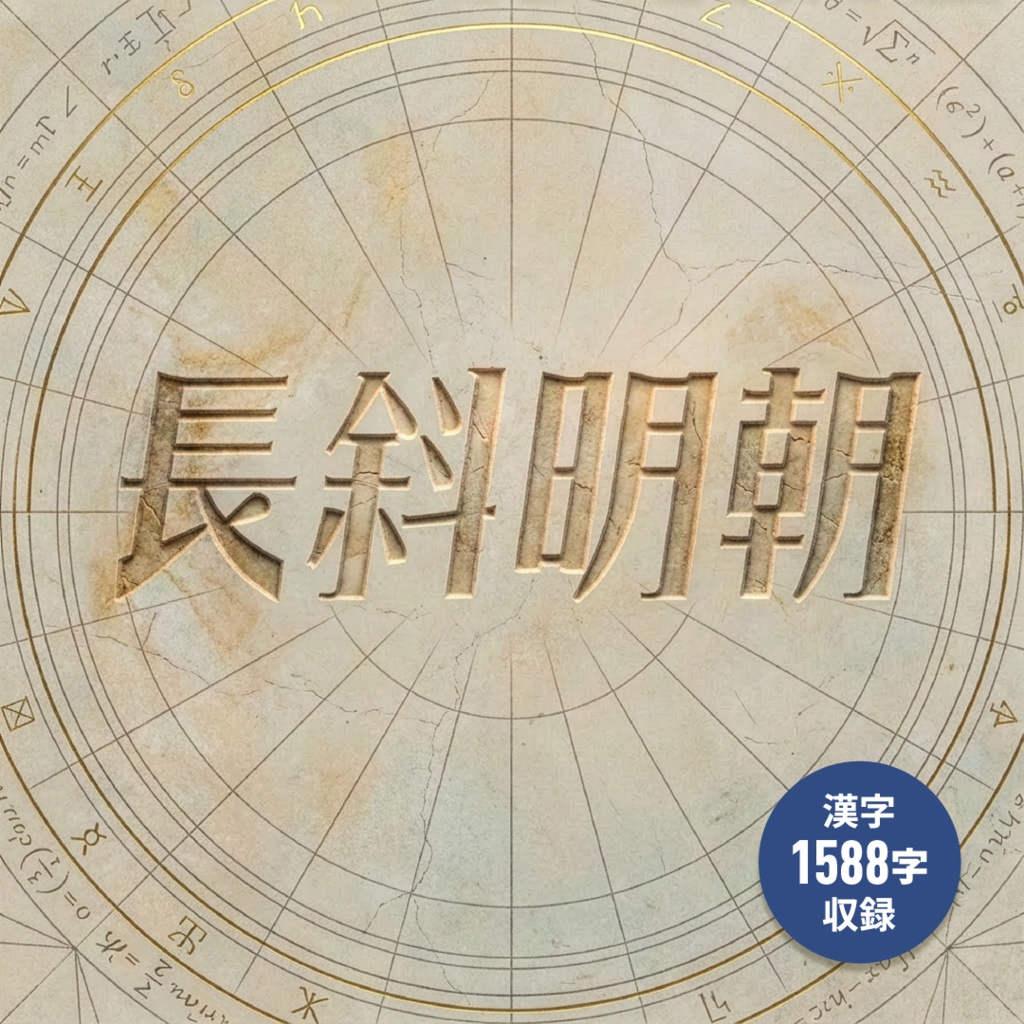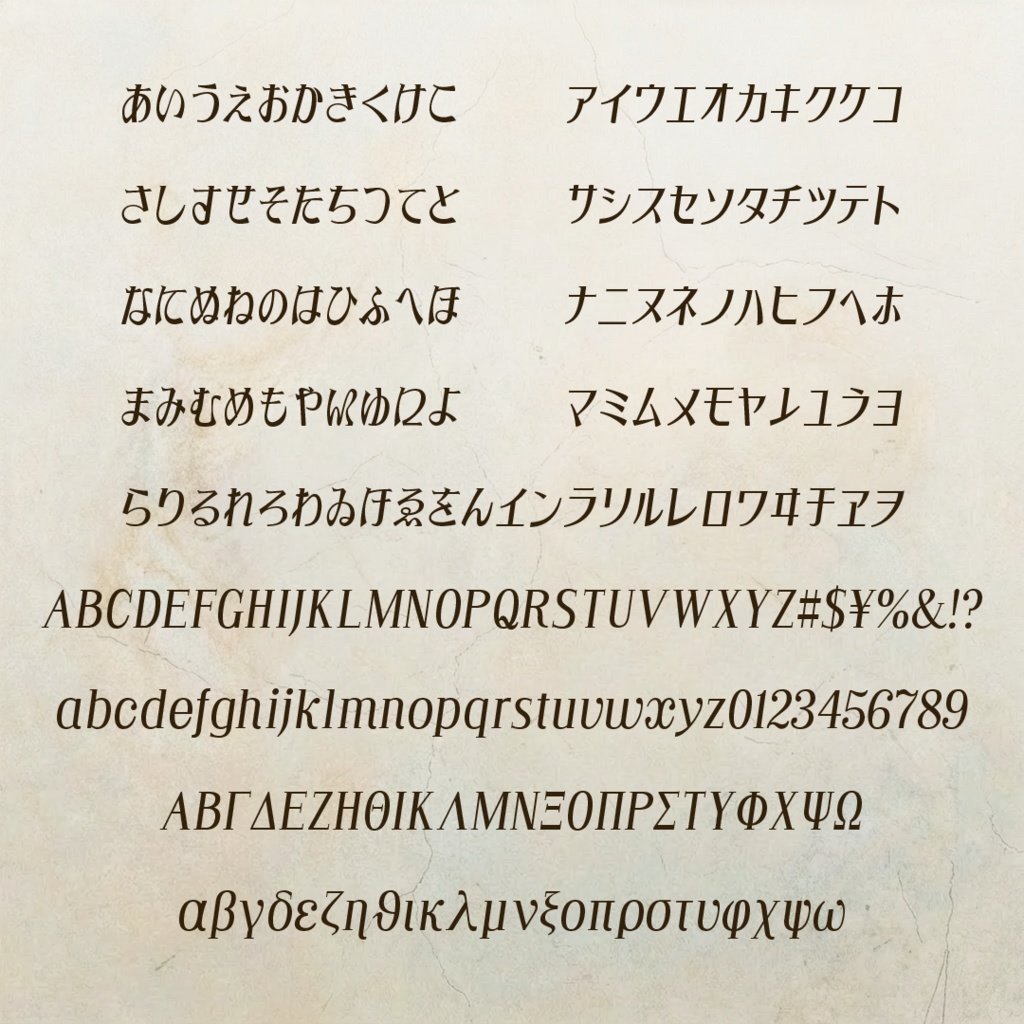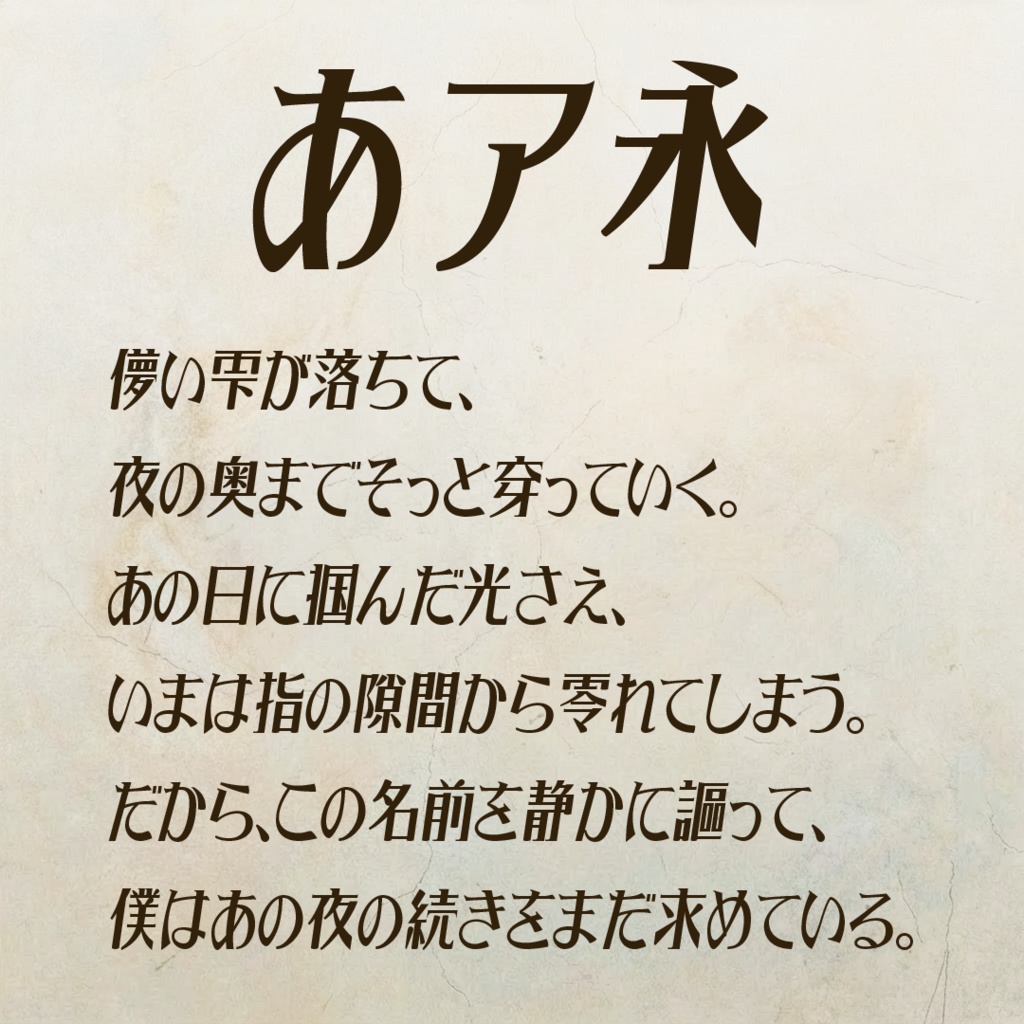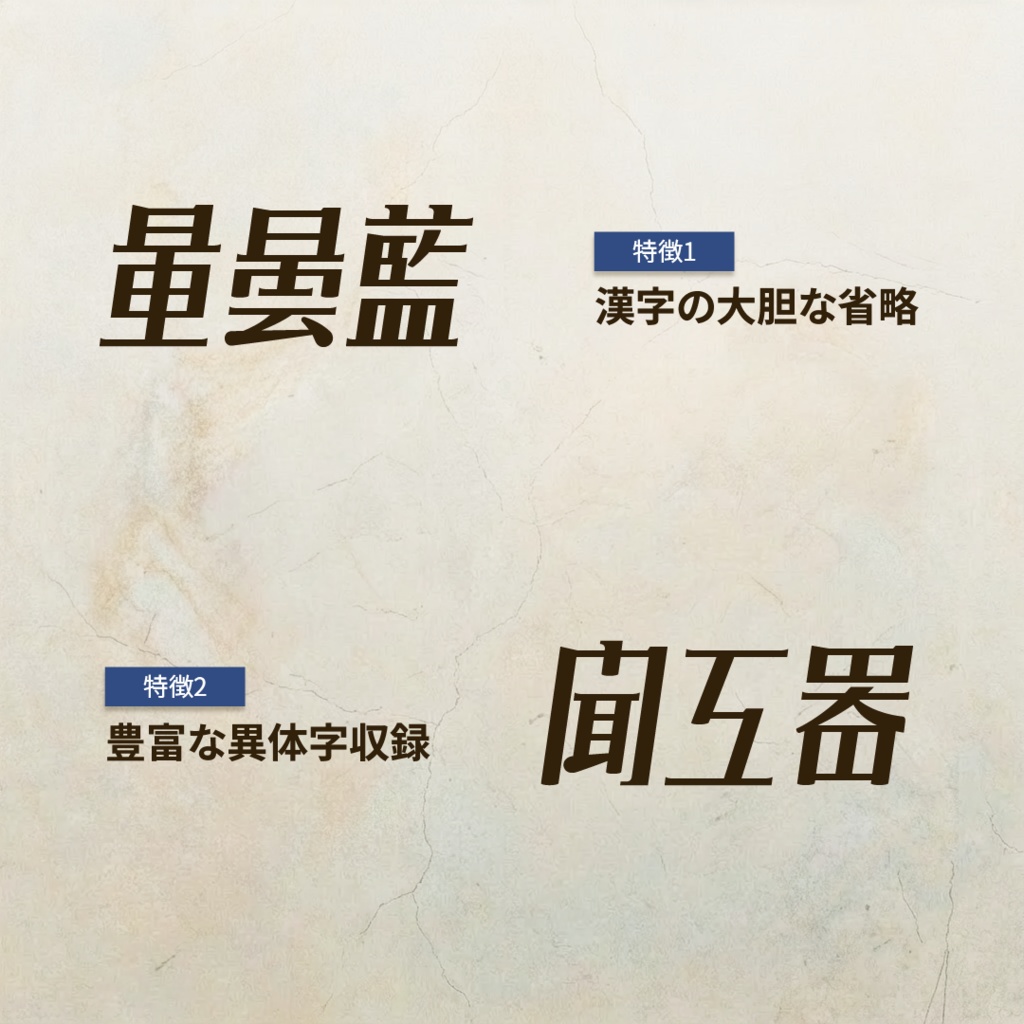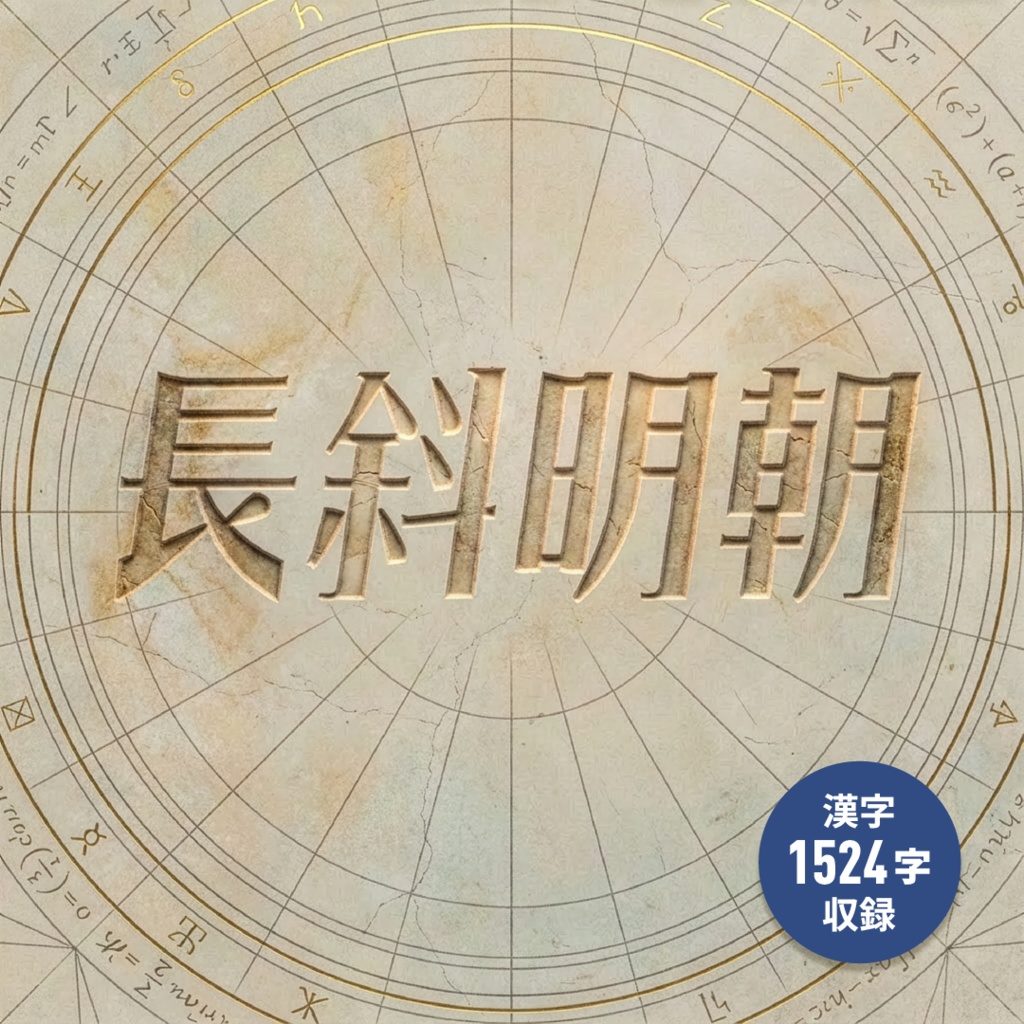
長斜明朝【フォント】
☀️🌴 SUMMER SALE 開催中!🌴☀️ \ 7/29〜8/12 23:59まで! / 通常価格:3,980円 🔥 セール価格:2,480円【37.7%OFF】 この夏だけのお得な価格をお見逃しなく!🍉✨ 横組用平斜体 明朝体〈昭和〉をベースに制作した横組用長斜体明朝体です。 縦組みには非対応です。 漢字には大胆な省略が施されています。 MV向けフォントとして制作しています。 収録漢字はMV用文字セットという独自文字セットで制作しているためまだ教育漢字を網羅していません。 【フォント仕様】 ・収録文字種 基本ラテン文字/基本ギリシャ文字/ひらがな/カタカナ/漢字1588字/その他記号等 2,134グリフ/2,078文字 収録 OpenTypeフォント / TrueTypeフォント 【利用規約】 当フォントをご利用された時点で、この利用規約に同意したものと見做します。 当フォントデータは、本規約に定める条件でご利用者様に使用する権利を許諾します。 当フォントの著作権やその他一切の権利はPalfに帰属します。 ●使用条件 1) 2人以上の複数人でご利用になる場合のみ、1ライセンスにつき端末3台までといたします。 2) 本フォントを使用して得られる結果については、仕様者自身が責任を負うものとします。 3) 一般印刷物の作成(ポスター、書籍、フライヤー等)にご利用いただけます。 4) 立体制作物の作成(ステッカー、Tシャツ、アクリルキーホルダー等)にご利用いただけます。 5) 映像及びWebに関連する制作物に於いては、画像化・アウトライン化した上でご利用いただけます。 6) ロゴマーク、タイトルデザインの作成にご利用いただけます。 7) 画像化・アウトライン化したものを加工・変形してご利用いただけます。 8) 購入者本人又は事務所内等での限定した使用に限り、当フォントファイルを改変し、本人のみが使用することができます。 ●禁止事項 当フォントファイルを使用する際、以下の事項を禁じます。 1) 第三者への譲渡・貸与・配布・販売 2) 当フォントデータを元とした、類似又は同一フォントのデータの作成 3) 公序良俗に反する目的、誹謗中傷目的での使用 4) 政治的・宗教的利用 5) 犯罪への利用 6) 当フォントのサーバー上へのアップロード 7) 当フォントデータを取り出すことができるソフトウェアへの組み込み ●その他 ・上記に記載されていない事項については、著作権法及び関連法規に従うものとします。 ・本利用規約は予告なしに変更されることがあります。